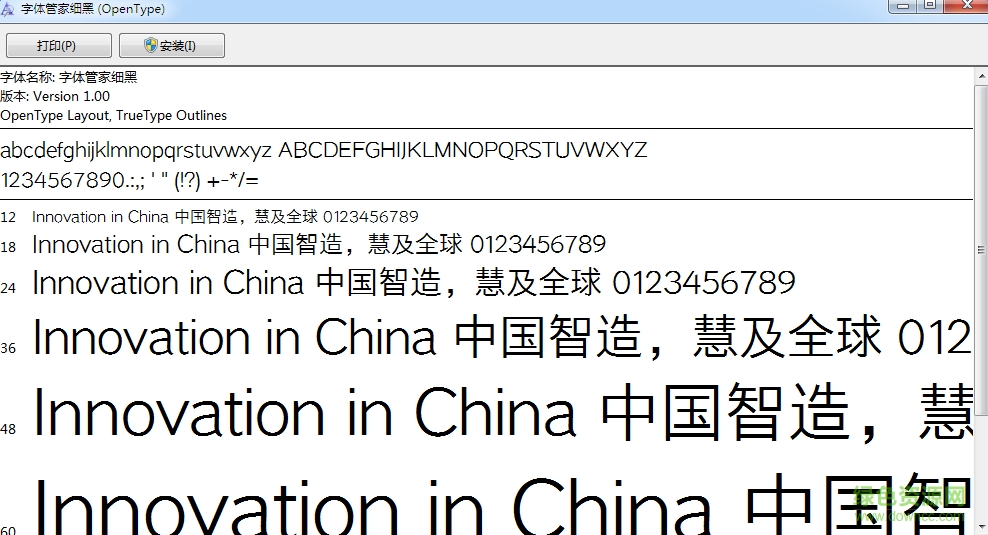
字體管家細(xì)黑體是在黑體基礎(chǔ)上減細(xì)設(shè)計而成,字形飽滿富于張力,筆畫硬朗簡潔表現(xiàn)清晰,特別是多字排在一起時,就可以展現(xiàn)出字形的連貫性和整體感,喜歡的朋友歡迎來綠色資源網(wǎng)下載使用!
字體管家細(xì)黑體字形結(jié)構(gòu)扁方、端莊,橫豎筆畫粗細(xì)比例適度、豎筆粗壯有力,布白均勻、行文貫通。粗細(xì)適中,比一般的黑體更清晰易讀,筆畫簡潔有力細(xì)微處變換靈動,即實用又富有裝飾效果。